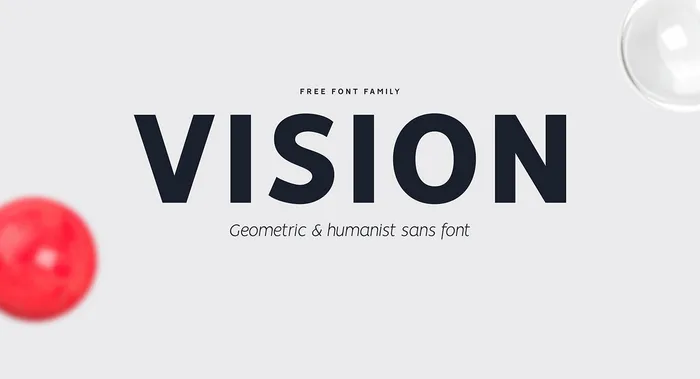
Vision Sans Font Family – Download Grátis
Vision Sans é uma família de fontes puramente geométrica, criada com a intenção de atender ao vasto espectro de necessidades do seu projeto de design. Ideal para trabalhos variados, essa família de 12 fontes foi inspirada no estudo das formas geométricas desenvolvidas por Vasily Kandinsky e na década de 1930, durante a criação de suas obras ‘Proun’. A influência dessas bases formadoras é perceptível em cada letra da família Vision Sans. Perfumado com uma extensão de ligaturas e recursos OpenType que garantem legibilidade e modernidade em qualquer tamanho de texto, esta fonte oferece um conjunto flexível de características que torna a adesão à sua identidade visual fácil e natural. Através da combinação perfeita entre geometria pura e modernismo clara, Vision Sans se destaca como uma opção ideal para uso tanto em grande texto quanto em pequenos detalhes, garantindo estética elegante e consistência visual ao mesmo tempo.